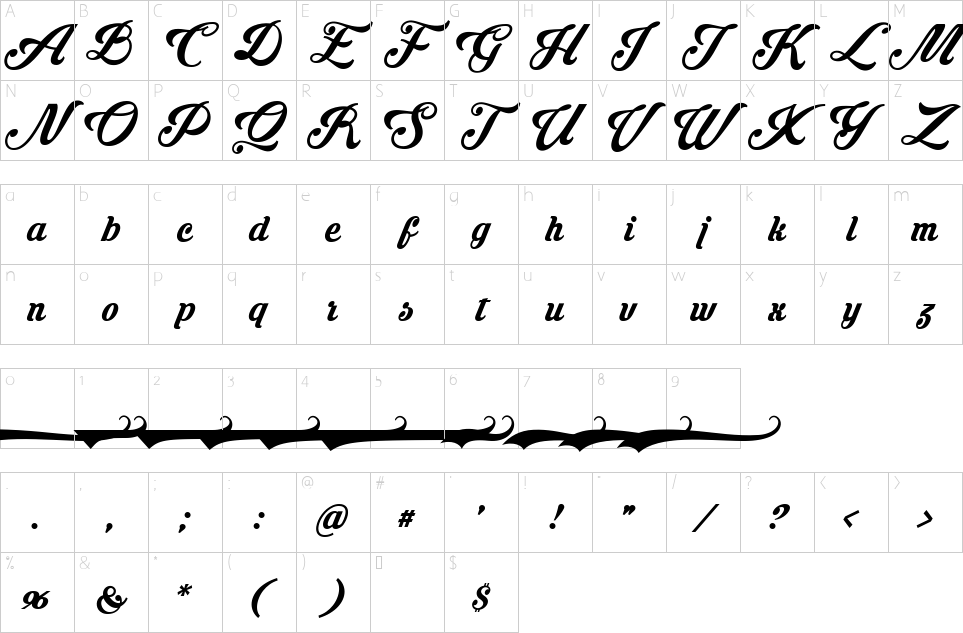
Descubra Krinkes, uma elegante e envolvente fonte gratuita que traz uma pitada de simplicidade ao seu design. Desenvolvida por Måns Grebäck, Krinkes está disponível tanto para sistemas Windows quanto Mac, com um design que combina elegância e minimalismo. Com sua elegância clássica e sutileza, Krinkes oferece uma alternativa perfeita para aqueles que buscam uma fonte única para projetos pessoais ou comerciais. Desde seu download inicial em 2020, a fonte Krinkes já foi baixada mais de 1.751.317 vezes, demonstrando seu valor e popularidade. Se você está em busca de uma fonte grata para adicionar ao seu portfólio, Krinkes é uma ótima escolha, combinando modernidade com simplicidade.